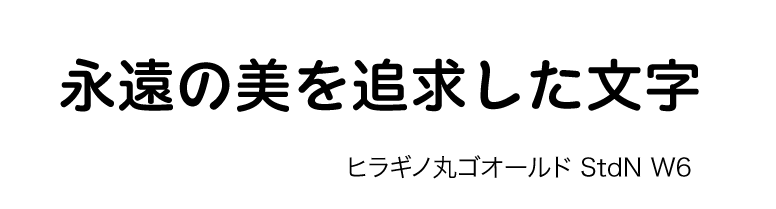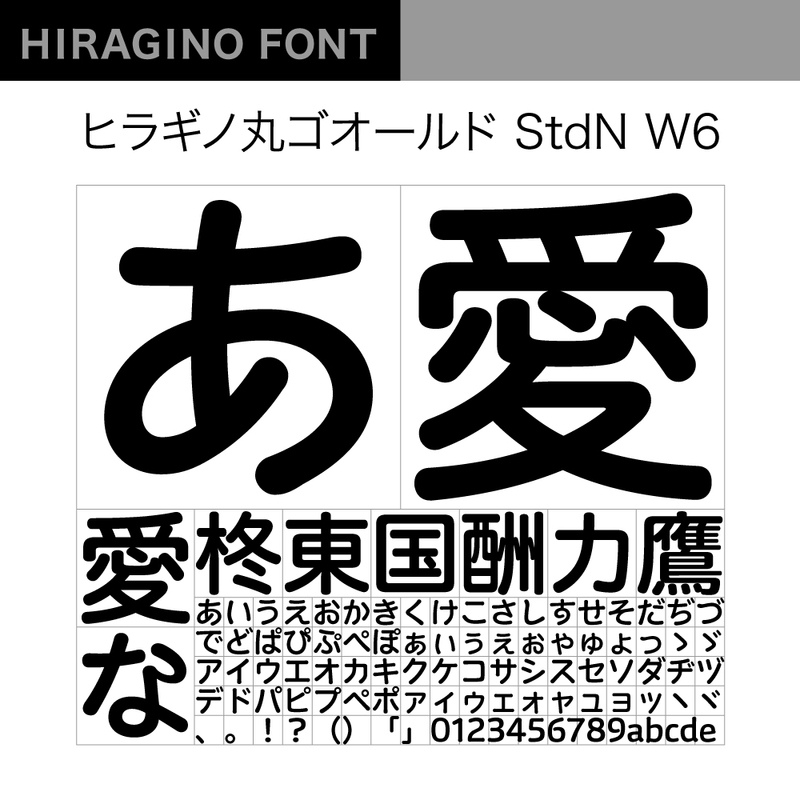
【ヒラギノ丸ゴ オールド】これまでにないユニークで個性的な丸ゴシック体です。_本の線の中に細太の抑揚がしっかりとついており、線端がぷっくりと太くなる独特のデザインが、単純に_えがちなカタカナなどの表情を豊かにしています。ひと_で惹きつける特徴を持ちながらも、親しみやすくどこか懐かしい独特のたたずまいがあり、タイトルや_出し、短い_章に使ってじっくり味わいたいフォントです。